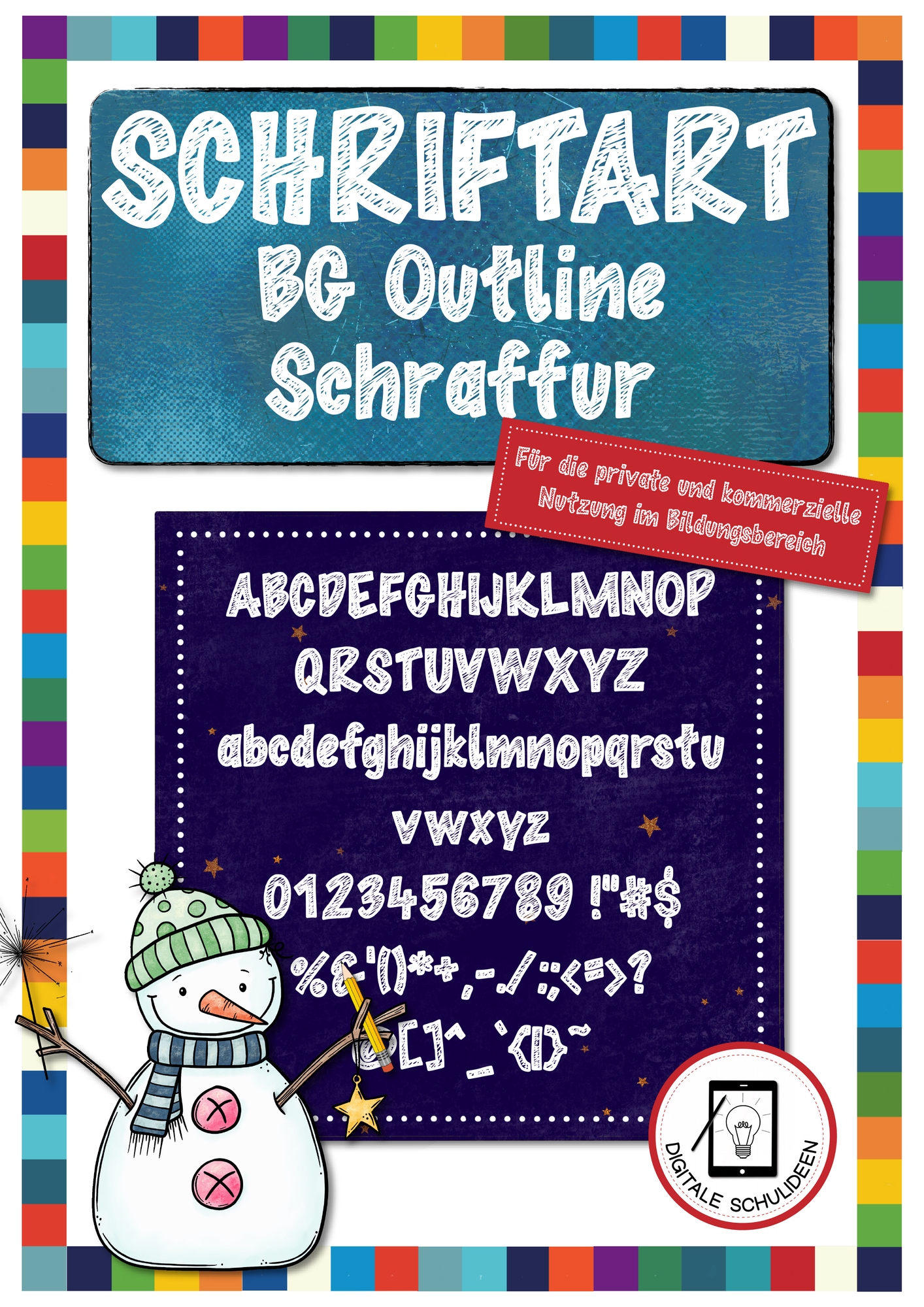
Tolle Schrift
Ich mag die Schrift sehr und nutze sie total gerne für Überschriften in meinen Materialen. Sie ist besonders, aber trotzdem für die Kinder gut lesbar. 👍
sehr schöne Schriftart
Schön gestaltete Schriftart, die ich gerne in meinen Materialien verwenden werde. Danke 😍
Schöne Schriftart
Ich benutze die Schriftart gerne für Überschriften. Tool ist, dass sie sich kommerziell nutzbar ihr.
Eine schöne Schriftart (Outline) zum Verschönern von Unterrichtsmaterial, welche auch zur kommerziellen Nutzung ist. Danke
Schriftart
Schöne Schriftart mit vielen Zeichen. Die Buchstaben erinnern mich an Schnee und Winter. Ich habe sie für mein Wintermaterial genutzt. Es ist wirklich schön damit geworden.
Ansprechend gestaltet!
Ich habe die Schriftart für den Bildungsbereich genutzt und bin absolut zufrieden damit! Die 236 Zeichen eignen sich sowohl für private als auch für kommerzielle Zwecke hervorragend und ansprechend.
Vielseitige Schriftart für kreative Projekte
Eine ansprechende Schriftart, die sich ideal für den Einsatz in Unterrichtsmaterialien oder kreativen Designs eignet. Klar gestaltet und gut lesbar – praktisch für kommerzielle Nutzung! ✍️